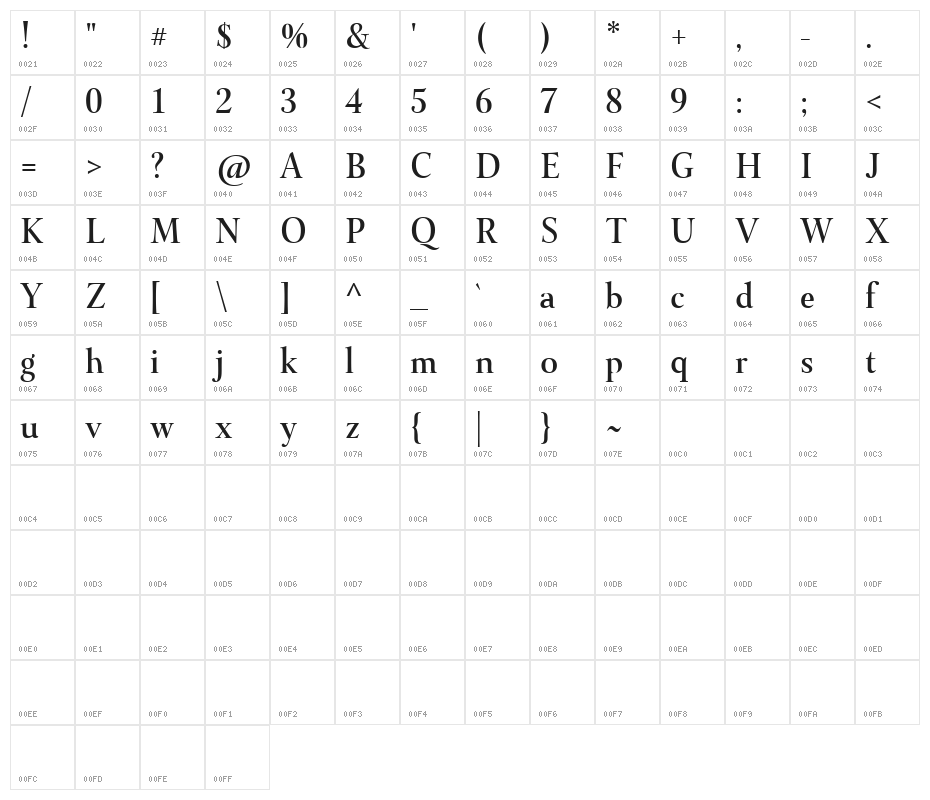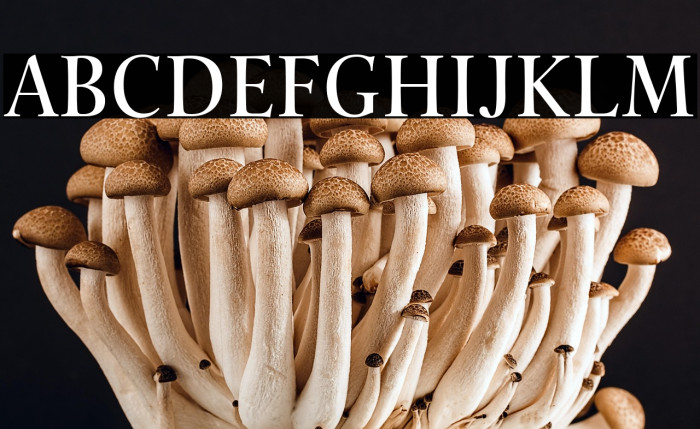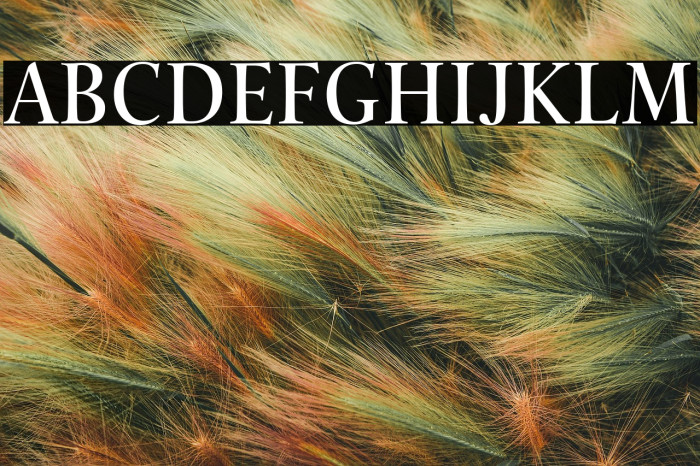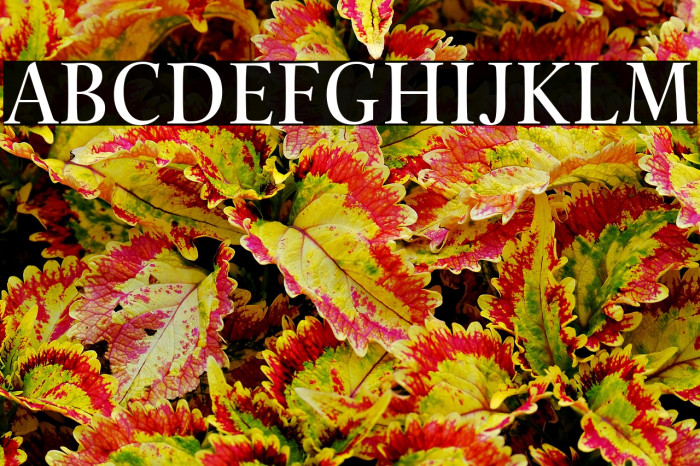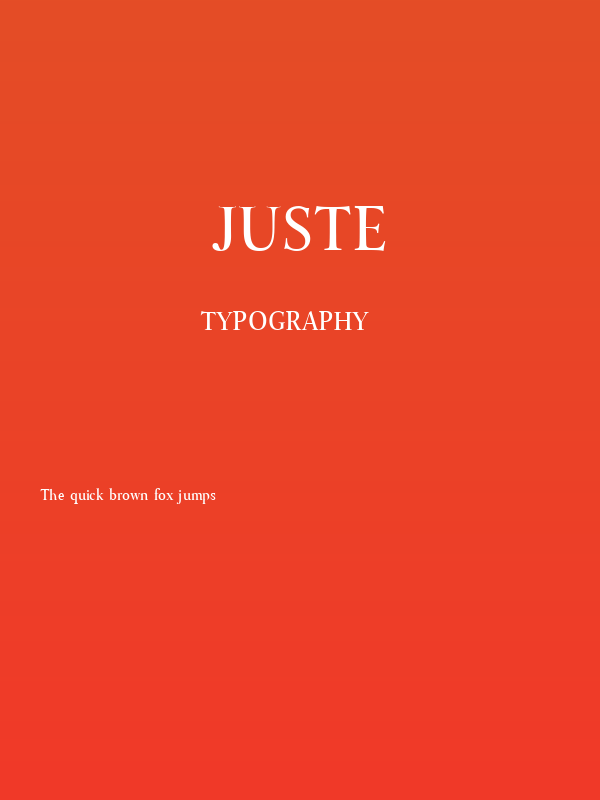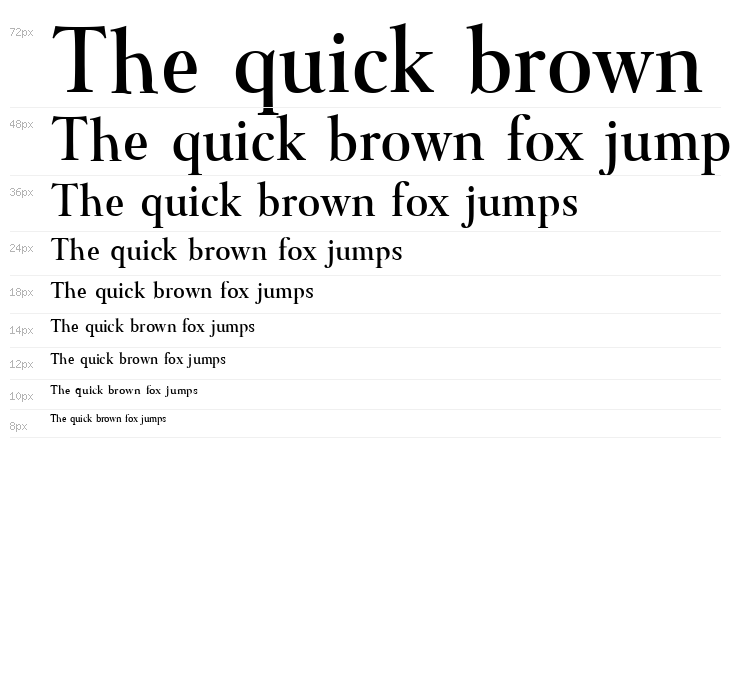
Juste Font
| Proiecte propuse | Ideal for editorial design, book covers, formal invitations, and branding projects that require a touch of elegance. |